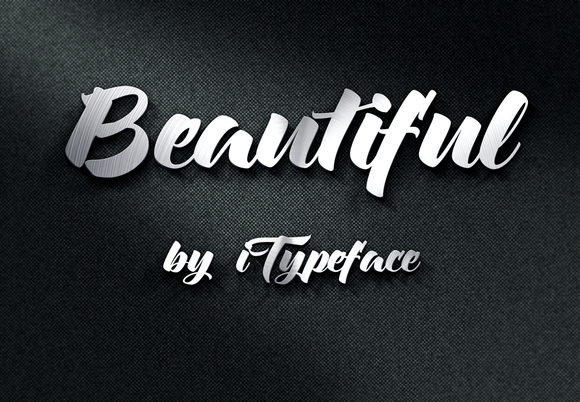
Beautiful Font – Download Grátis
Beautiful Font é uma fonte escrita à mão inspirada nos estilos do calligrafia com suas influências no estilo itálico e na técnica de caneca de penas. Inspirado nos métodos de expressão artesanal, a fonte começa com traços simples e contrastados desenhados em papel utilizando uma caneca de pena e marcador. Este projeto leva aos artistas e designer um recurso para explorar diferentes estilos de escrita à mão, fornecendo flexibilidade em vários aplicativos. A Beautiful Font é perfeita tanto para criações digitais quanto presenciais, trazendo um toque único e aconchegante às suas obras finais.